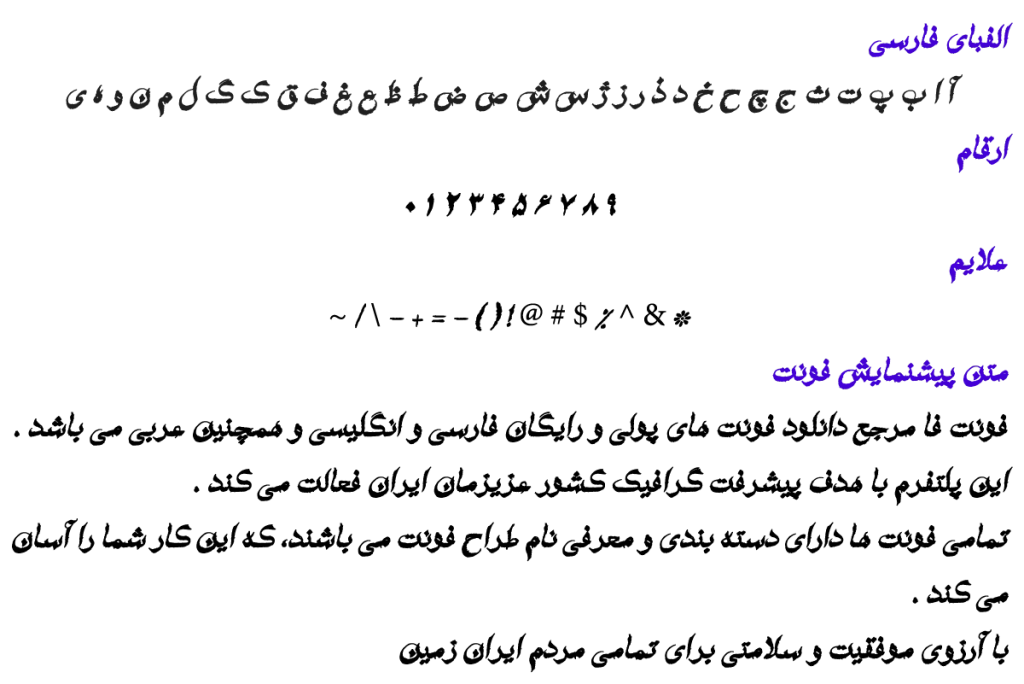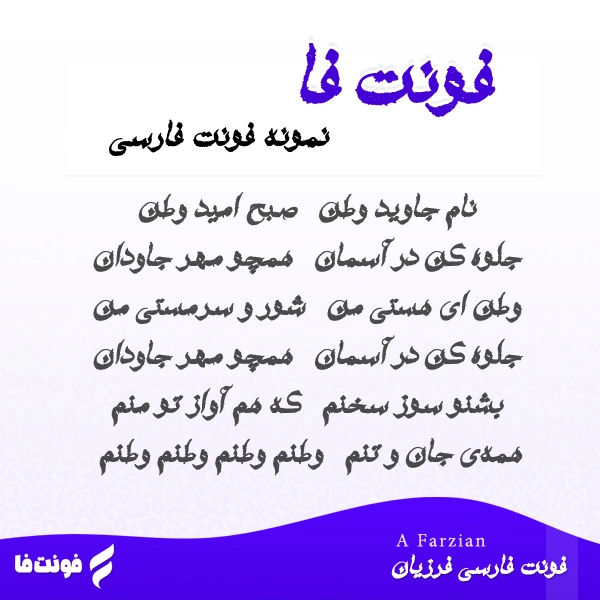
فونت فارسی فرزیان – A Farzian
سال ساخت فونت: 1392
طراح فونت: ابراهیم شفیعی نوع فونت: فونت گرافیکی
پیشنمایش فونت فرزیان
توضیحات و معرفی فونت فرزیان
فونت فارسی فرزیان ( A Farzian ) از مجموعه فونت های آزاد می باشد، و نیز نوع فونت گرافیکی می باشد.
فونت خوشگل مربوط توسط سید روح الله میرمحمدی در سال 1392 طراحی و ساخته شده است.
و نیز فونت A Farzian در یک وزن معمولی است.
شعر زیبای «وطنم» را که با این تایپ فیس نوشته شده، می توانید در تصویر زیر ببینید.